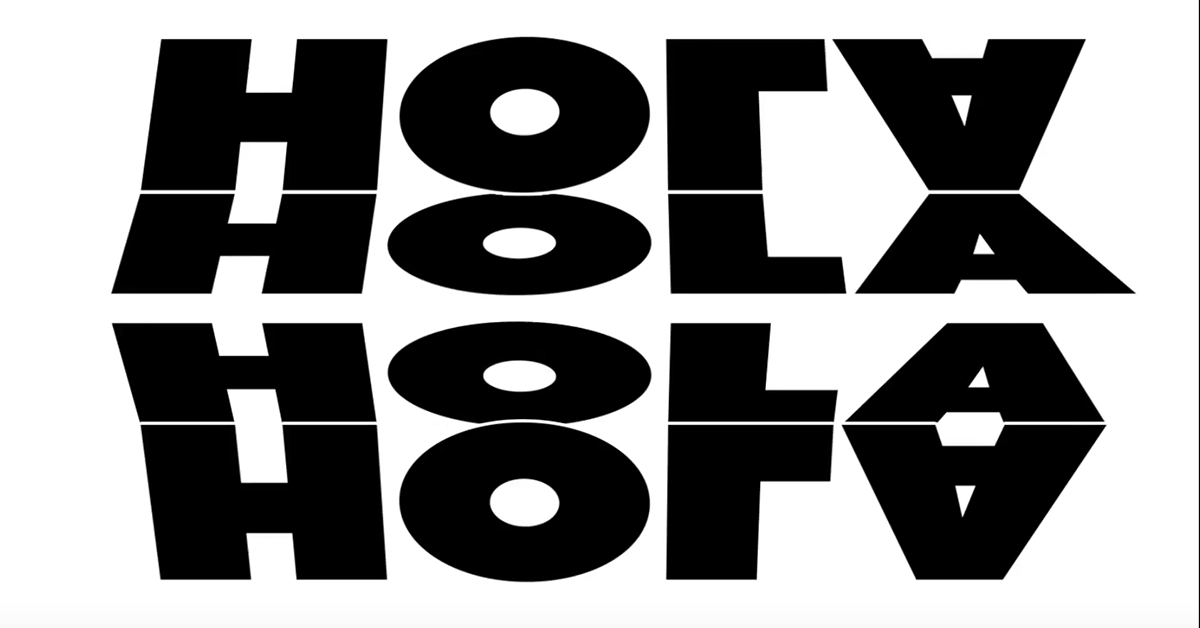
5 espectaculares proyectos de tipografía animada
Holke 79 comparte contigo ejemplos de tipografía experimental en movimiento
Borja Holke, también conocido como Holke 79 (@holke79), es un diseñador gráfico y motion designer con más de una década de experiencia en proyectos de animación. Trabaja composición digital, animación 2D y 3D, así como proyectos de tipografía animada, storyboards y publicidad.
Hoy comparte contigo cinco exponentes de la tipografía animada experimental que te mostrarán los alcances que puede tener esta disciplina creativa. ¿Cuál es tu favorito?
Nikita Iziev
Este diseñador basado en el Reino Unido se enfoca en la intersección entre la tipografía, el movimiento y el diseño gráfico. Se caracteriza por un estilo elegante en blanco y negro, cuya intención es borrar las fronteras entre lo analógico y lo digital.
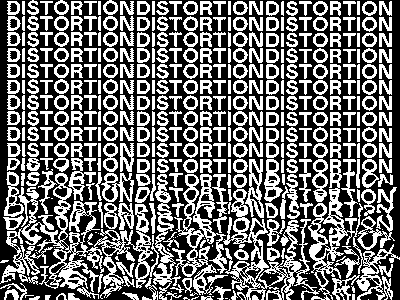
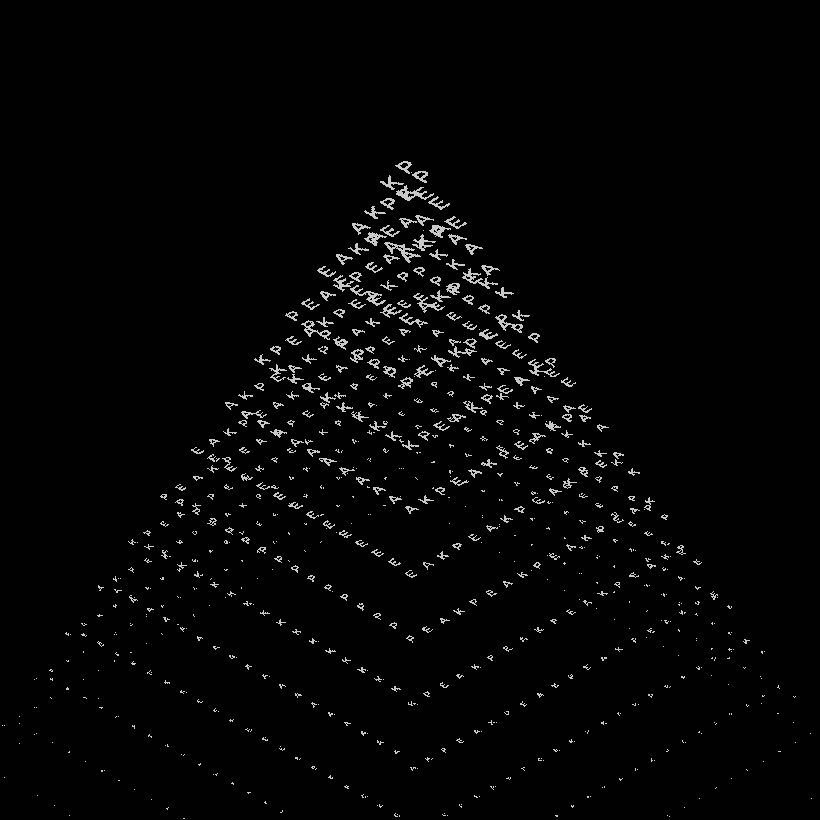
Kurppa Hosk
Con base en Suecia, es una agencia internacional de branding que diseña estrategias para marcas y organizaciones. Su enfoque combina la investigación de marca con la belleza y audacia de lo artístico.
Mother Design
Es un estudio independiente de branding y diseño que, en sus palabras, “se especializa en la no-especialización”. Trabajan en proyectos que van desde arquitectura de marca y diseño experimental, hasta el diseño sonoro y la dirección de arte.
Pangram Pangram
Es un proyecto del diseñador Mathieu Desjardins, cuyo objetivo es dar acceso libre de uso de tipografías de calidad, en especial pensado para los diseñadores. “Sentimos que el mayor número posible de personas debería poder compartir, ver y usar nuestras fuentes”, afirma.
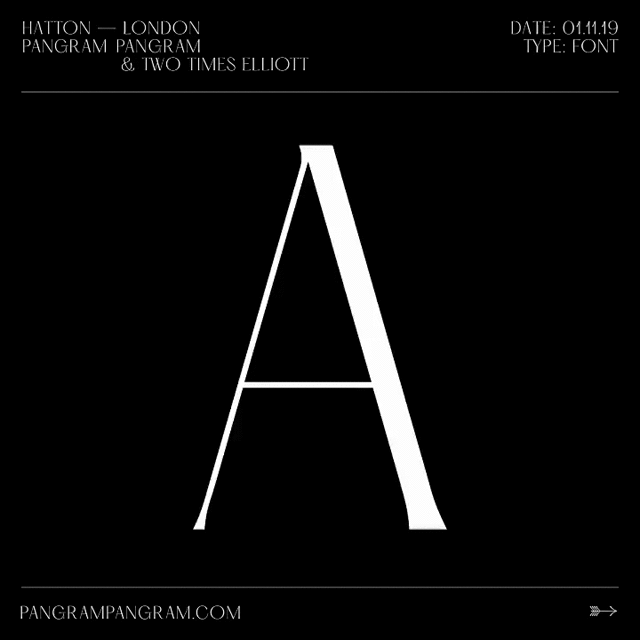
Atipo
Este estudio independiente de diseño y tipografías digitales está basado en España, y lo establecieron Raúl García del Pomar e Ismael González. En su sitio apoyan estudiantes, diseñadores.y agencias con fuentes gratuitas y a precios asequibles.